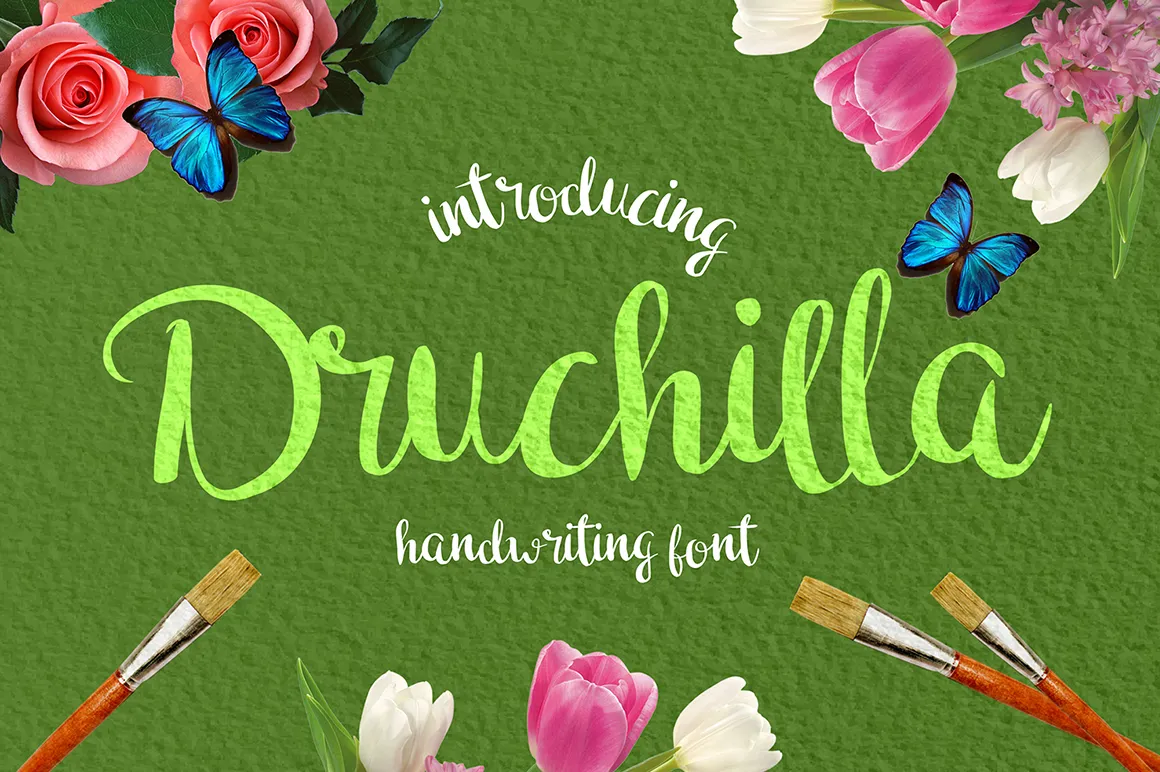
Druchilla Script Font – Download Grátis
Olá! Bem-vindo à página onde você pode baixar a fonte “Druchilla Script Font”. Esta é uma opção gratuita que apresenta linhas elegantes e fluidas, perfeita para adicionar um toque de arte à sua criação. A fonte foi criada pelo designer madeDeduk, um talento no campo do design gráfico. Se você gostou desta fonte e quer ter mais opções gratuitas ou comerciais, recomendamos que visite o site da Creative Market e Font Bundles para explorar ainda mais os recursos oferecidos por este designer incrível. Além disso, se tiver alguma dúvida, sinta-se à vontade para nos contactar diretamente. Estaremos felizes em ajudá-lo a encontrar respostas às suas perguntas. Para aqueles que desejarem uma versão full, o criador oferece a opção de fazer um pequeno donativo através da sua plataforma de crowdfunding. Todos os recursos são muito apreciados e contribuem para manter este rico acervo de fontes gratuitas e comerciais disponíveis para todos nós. Fiquem à vontade para explorar mais o trabalho deste designer talentoso e encontrar novos projetos inspiradores no seu Instagram, aqui: https://www.instagram.com/acekelgondolayu/?hl=en.